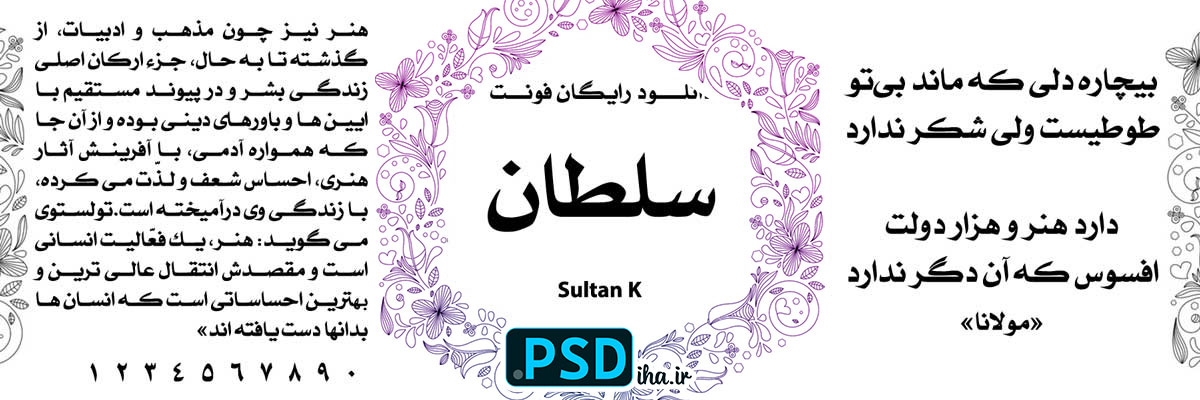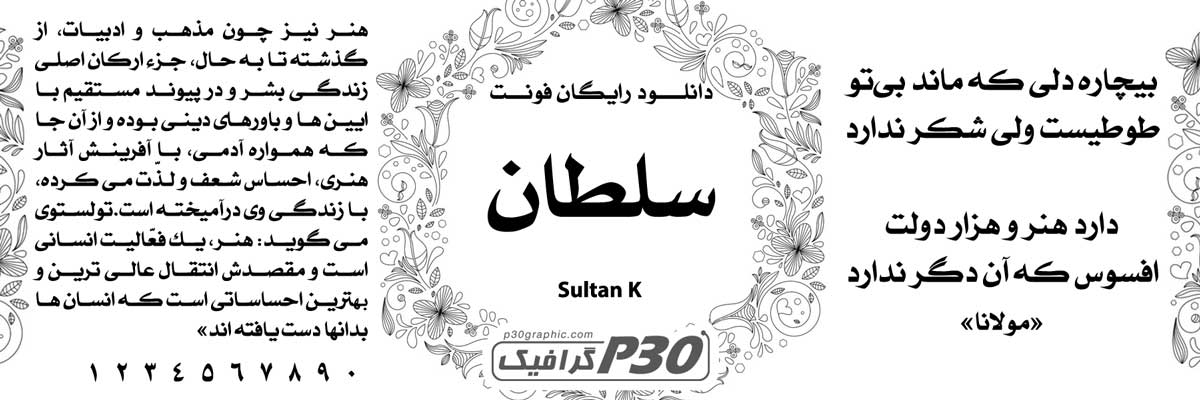
فونت سلطان
سلام دوستان خلاق! اگه مثل من عاشق طراحی‌های حرفه‌ای هستید و همیشه دنبال فونتی می‌گردید که هم شیک باشه و هم با سلیقه ایرانی جور دربیاد، حتماً فونت سلطان رو امتحان کنید. من خودم تو پروژه‌های چاپی‌م، از کارت ویزیت‌های لوکس گرفته تا تراکت‌های تبلیغاتی پررنگ، بارها از این فونت استفاده کردم و هر بار نتیجه‌ش شگفت‌انگیز بوده. فونت سلطان، با الهام از خطاطی سنتی ایرانی، یه حس اصیل و مدرن رو همزمان به کارهاتون می‌ده. تصور کنید لوگوی کسب‌وکارتون با این فونت، چقدر چشم‌نواز و منحصربه‌فرد می‌شه – انگار یه تکه از تاریخ رو با طعم امروزی سرو کردید!
چرا فونت سلطان انتخاب اول طراحان چاپیه؟
فونت سلطان نه تنها برای متن‌های فارسی و عربی عالی عمل می‌کنه، بلکه انعطاف‌پذیری‌ش تو ترکیب با المان‌های گرافیکی دیگه، بی‌نظیره. این فونت رو طراحان حرفه‌ای برای پروژه‌های چاپی مثل کارت ویزیت، تراکت، لیبل محصولات و حتی بنرهای تبلیغاتی پیشنهاد می‌کنن. دلیلش؟ خوانایی بالا در اندازه‌های مختلف، از تیترهای بزرگ تا متن‌های ریز، و سازگاری عالی با نرم‌افزارهایی مثل ایلاستریتور و فتوشاپ. من یادمه یه بار برای یه مشتری که می‌خواست لیبل بسته‌بندی‌ش خاص باشه، از فونت سلطان استفاده کردم و سفارش‌ش انقدر خوب چاپ شد که حالا مشتری دائمی‌مونه!
این فونت در سه وزن مختلف عرضه شده تا بتونید بسته به نیاز پروژه‌تون انتخاب کنید:
• Sultan K Light: وزن سبک و ظریف، ایده‌آل برای متن‌های ظریف و لوگوهای مینیمال. وقتی می‌خواید حس لطافت و ظرافت بدید، این وزن معجزه می‌کنه.
• Sultan K Medium: وزن متوسط و متعادل، همه‌کاره‌ترین گزینه برای بدنه متن‌ها. تو تراکت‌ها و کارت‌های ویزیت، این وزن تعادل عالی بین خوانایی و جذابیت ایجاد می‌کنه.
• Sultan K Bold: وزن جسور و قوی، برای تیترها و عناوین برجسته. اگه می‌خواید توجه مخاطب رو جلب کنید، این وزن مثل یه فریاد هنری عمل می‌کنه!